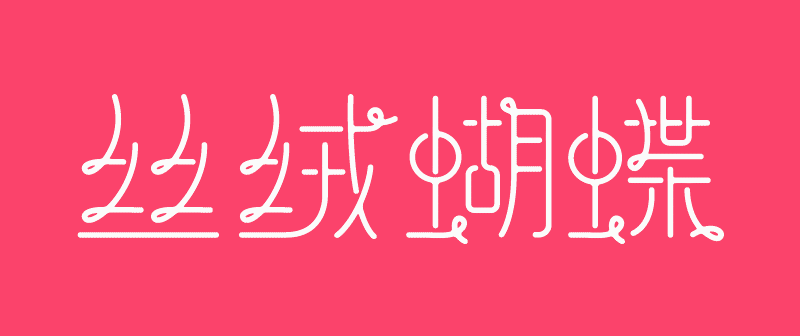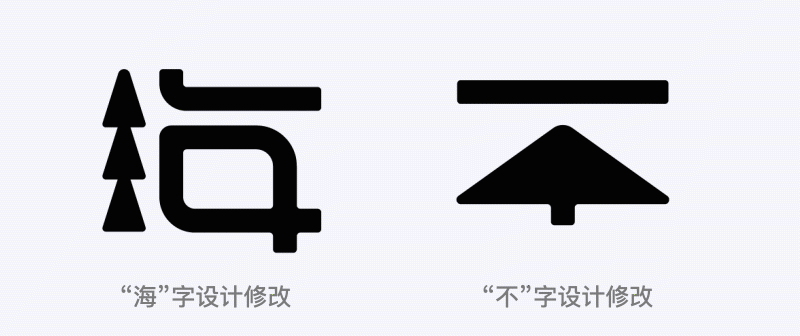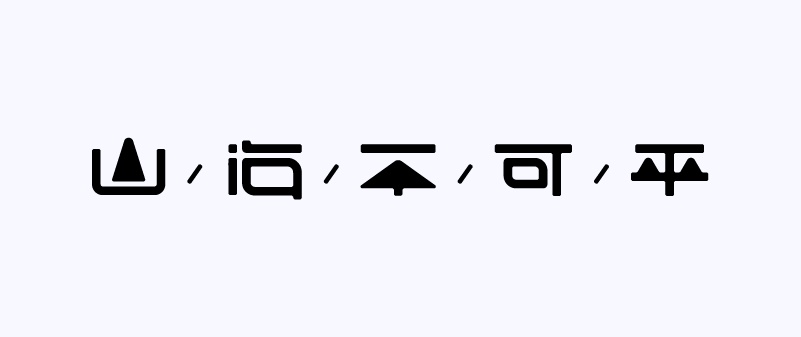
11款字体设计的全过程案例
做字流程
三大原则
下图是11款字的汇总(有些是有两个方案),大方向的做字流程就是上面提到的。不过我做字其实有好几套不同的方式方法和流程。下面让我们进入具体字体案例的分析中吧。
第6款
1. 绘制手稿
草稿工具从来不受限,且不同工具的草稿各有千秋。比如直接在 AI 里用铅笔工具绘制,也是一个不错的选择。这里大概绘制出这组字体的基本形态。
2. 字库字体结构参考
3. 雏形
快速用钢笔工具按照上面绘制的手稿的样子,绘制出字体的基本轮廓。
• 字体风格,我想让它拥有线条缠绕的感觉。
• 颜值笔形(即这组字体的极富特征的笔形)是笔画转折处的扭转样式。
4. 初稿
上一步骤中的字体笔形特征并未在整组字体中匀称分布使用。比如「绒」字右上角的横笔末端转圈圈的处理就略显不足。
所以「绒」字右上角的横笔末端处理成扭转样式。
5. 调整
这个阶段这组字是存在大量问题的,下面一步步调整优化。
调整「丝」字倾斜笔画的弧度,以及该字四处笔画转折处的扭转处理。「丝」字先前过于倾斜,一来字体缺失美感,二来造成「丝」字外轮廓视觉上不完整。)
「绒」字绞丝旁倾斜笔画的弧度,以及该部分两处笔画转折处的扭转处理。
「蝶」字「世」部分的笔形路径修改,让其更符合整组字体的设计风格。
6. 继续调整
笔画转折处的扭转处理是整组字的颜值笔画,是特色部分,该特征应该均衡分布在整组字体当中,才会看起来和谐。上图中的「蝴」字就感觉颜值笔画少了一些,继续修改。
• 「蝴」字「月」部分加入了颜值画笔。
• 「蝴」字「古」部分的圆形,改成方形,加断笔处理。原因是在最后两字当中,有三个圆形,显得累赘。
7. 化繁为简
「蝴」字和「蝶」字,「虫」部分圆形与竖笔相交,交汇处越多就越显得该字的视觉重量加重,从而造成整组字的不和谐。
因此化繁为简:
• 对「蝴」和「蝶」的「虫」部分做断笔处理,减少了笔画交汇黑点,增加了呼吸感。
• 同时为了呼应上一步的操作,对整组字的其他部分也在合适的位置做断笔处理。
• 「蝶」字的「世」部分最左边的竖笔,由直变成弧,更具美感,且与「丝」字的弧笔画呼应,整体上更和谐了。
• 「蝴」字「月」部分在上一步骤中加入的颜值画笔,经审视发现还是有些过度设计了,去掉又不行,因此要做到既保留这种特征的印象,又要弱化其设计感,于是做了下图的处理。做到:有但不抢,点到为止。
• 「蝴」字右下角增加了颜值画笔,让该字在整体视觉更显和谐。
8. 做「溢墨」处理
9. 最后优化
• 对「绒」字右下角的撇笔与捺笔交汇处做断笔处理。
• 「蝴」字的「月」部分,中间的两横笔,在上一步骤是在左边做断笔处理,这里修改在右边断笔,符合了整组字的断笔处理方式。(几乎所有断笔都在竖笔画的左边,即「月」字或其他字横笔画的右笔端留白)
• 「蝶」字的右下角「木」部分横笔也一样做断笔处理。
无论是断笔处理,还是调整断笔的方向或位置,目的只有一个,就是调整整组中的视觉均衡。可以把整组字看作是图形排版,我们要做到单一字当中笔画在确保识别的前提下做到有美感、符合整体风格;而整组字体间,也要做到疏密均衡,方能达到视觉重量的一致。
10. 做字全流程GIF图
把过程用动效串起来,方便大家快速有效感受字体设计过程的变化。
11. 包装
第7款
1. 绘制手稿
2. 字库字体结构参考
3. 绘制字框与网格
有字框与网格作为参考辅助设计,更加有保障。
4. 初稿
这是一款几何图形化的字体设计风格。我用抽象的三角形与直线条搭建整组字的结构。三角形,可以是山峰,比如下面的「山」字;也可以是小山丘,比如「平」字;或者可以是树,比如「海」字左边部分三角形堆叠起来的样子。
几何图形化字体中的抽象形,可以完美将字体笔画与事物形态融为一体,这是它最妙的地方。
5. 加一些装饰线
在字体之间加入一些装饰线,显精致。
6. 样式分布需均衡
上一步骤的字体呈现,排版拉开,加装饰线之后确实精致了,不过在视觉上还是有些奇怪。比如我把上面的字体分为两种,一种是图形占比大的,当成是实心圆;一种是图形占比小的,当成是空心圆,那么上面的字体就会是:实 | 空 | 空 | 空 | 实,这样的样式分布就不太合理,在五个字一组当中,只有两边是实心字,几何图形字体的氛围其实并没有营造出来,这样呈现的字体气质就会很怪。
应该是:实 | 空 | 实,这样的样式分布就合理一些,更均衡,就好比音乐一般有节奏感。
因此,我想办法针对「不」字做调整,将其由空变实,且融入三角形。
7. 调整
「海」字在上一步骤,左边的三点水是三个三角形堆叠起来,为之树,但显得拥挤,所以去掉一个三角形,加上一个小圆形。好似树梢上有一太阳。
「海」字的「母」部分整体向上收,整个字中宫内收。感觉跟其他字变得不是很搭了。
「不」字在上一步骤感觉整个字太宽,通过对该字与整组字体的观察,发现该字的视觉重量过重,其实就是三角形部分太宽大。因此收紧处理。
「可」字,上一步骤中宫过于内收,主要是「口」部分太小了,固将中间的「口」部分外扩,填满字框,做到中宫外扩,字形饱满。
8. 继续调整
调整完一遍后,我会不断观察每个单一字体识别是否足够、字体结构是否合理舒服、字体个性是否保证不缺失,然后再整体去观察,衡量标准跟观察单一字一样,还要观察字与字之间的合理性。
• 「可」字经观察比对,中宫外扩太猛,所以往回收敛一下;然后其右上角和左下角的圆角弧度也加大了一些。
• 「海」字三点水旁还是不对,样式有些过度设计,因此决定放弃这个样式,用简约线条。得到的结果是:山,面形+线条;海,线条;不,面形+线条;可,线条;平,面形+线条,更符合前面提到的音乐节奏般的合理样式分布。
不足的地方就是「海」字的视觉重量还是重了。
9. 接着调整
「海」字三点水旁做了调整,如图。
10. 继续优化